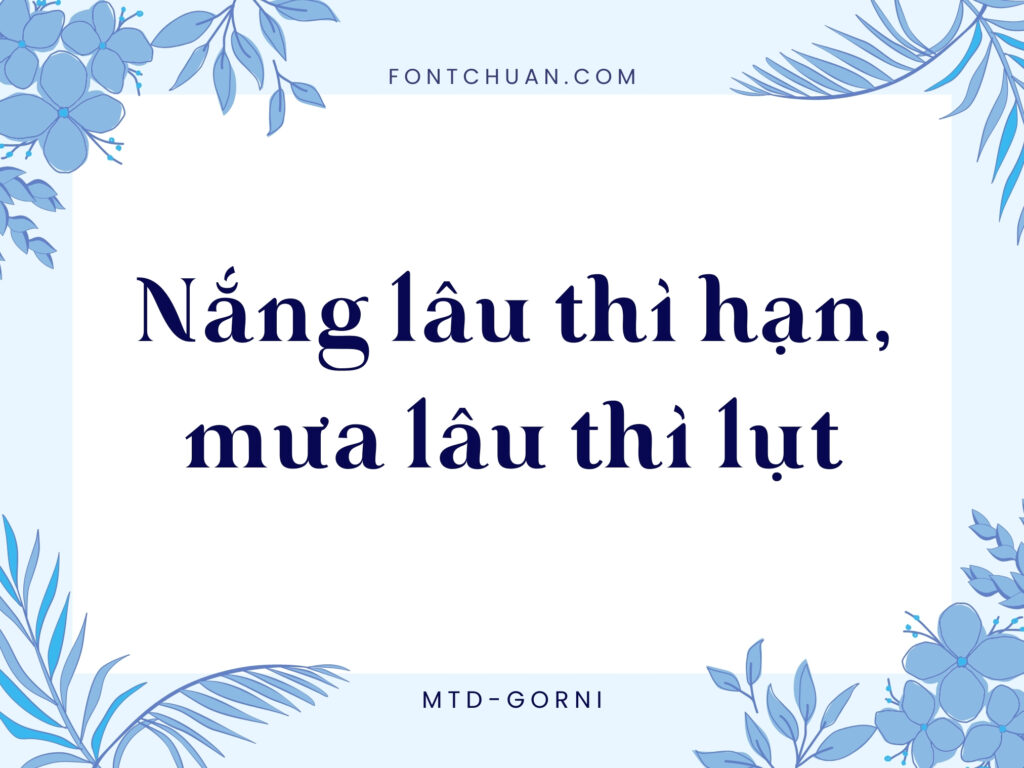
Font MTD Gorni Việt Hóa
Font MTD Gorni là một phông chữ serif hiển thị với phong cách lãng mạn, được thiết kế bởi MaGo và phát hành trên FontBundles. Font đã được Việt hóa bởi Mộc Hạ, hỗ trợ tiếng Việt và hơn 90 ngôn ngữ khác, giúp mở rộng khả năng ứng dụng trong các thiết kế đa ngôn ngữ. Đây là một trong những phông chữ được cộng đồng thiết kế đánh giá cao và ứng dụng trong nhiều dự án sáng tạo, đáp ứng nhu cầu đa dạng của người dùng.
MTD Gorni nổi bật với các ký tự đặc biệt và ligature, mang đến sự độc đáo và khác biệt cho văn bản. Font rất phù hợp cho các thiết kế tiêu đề, áp phích, thiệp mời và các ấn phẩm yêu cầu sự tinh tế và sáng tạo. Các ngành nghề phù hợp bao gồm quảng cáo, giáo dục, công nghệ, thiệp cưới và ảnh cưới. Font này cũng lý tưởng cho các sự kiện như Tết, Giáng sinh, Valentine và các lễ hội khác.